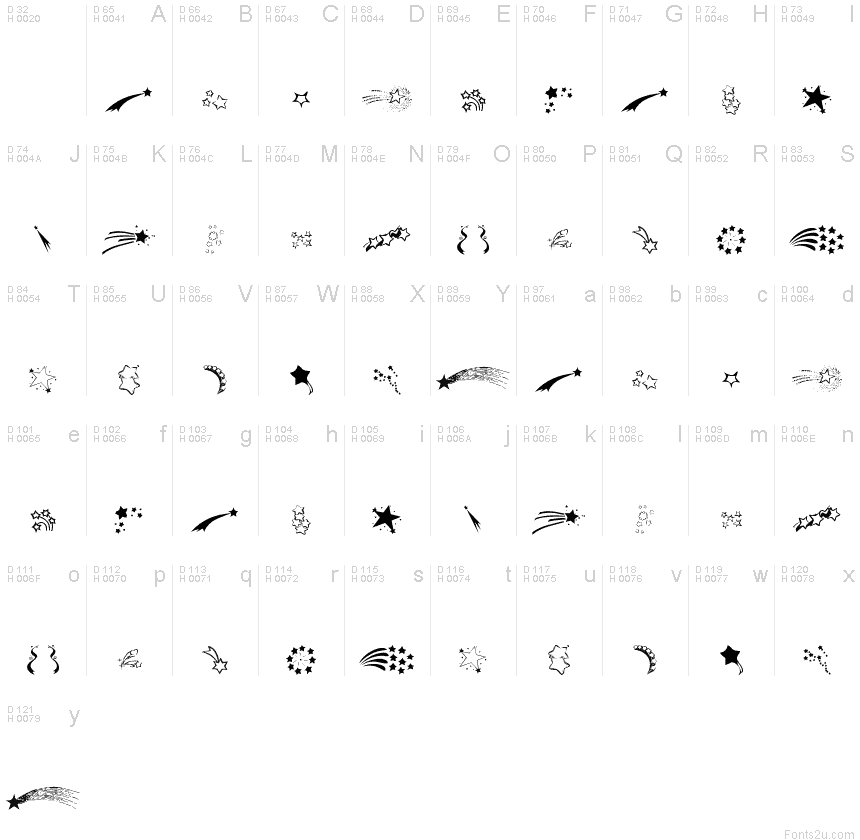
KR Starry Eyed di Kat Rakos è un font dingbat gratuito a tema stellare, incentrato su esplosioni, gruppi e scie di stelle cadenti piuttosto che su semplici simboli isolati. Il set ripropone stelle a cinque punte in versioni piene, contornate e con effetto scintilla, creando un ritmo festoso e celeste che risulta coerente in tutta la collezione.
Inviti per feste, schede di valutazione scolastiche, pagine di scrapbooking, creazioni artigianali e didascalie: tutti questi elementi possono utilizzare queste icone come bordi, decorazioni angolari o veloci riempitivi. Il mix di archi di comete, mini stelle sparse e forme più grandi aggiunge movimento ai layout, perfetto quando una pagina statica ha bisogno di un semplice accento celeste.